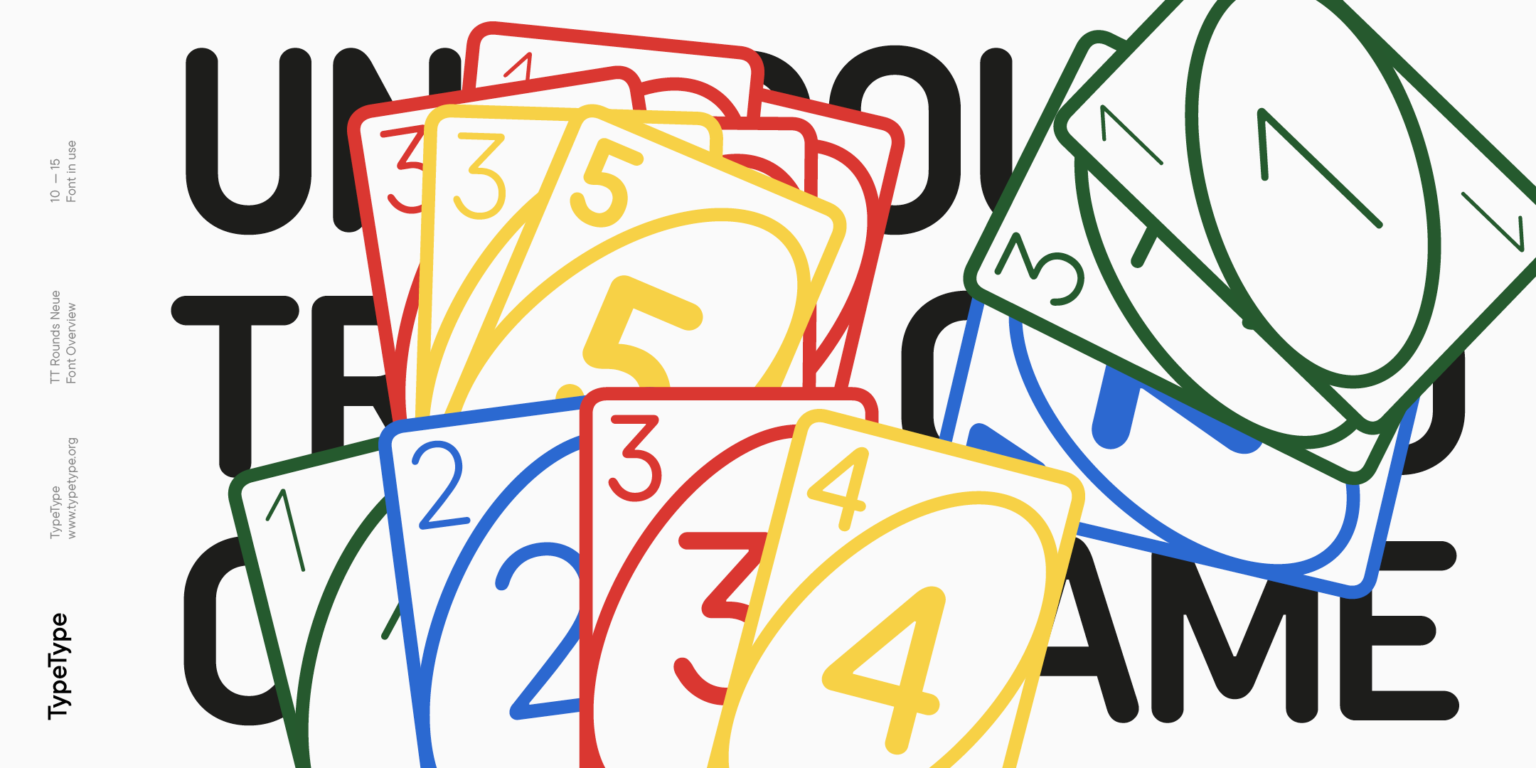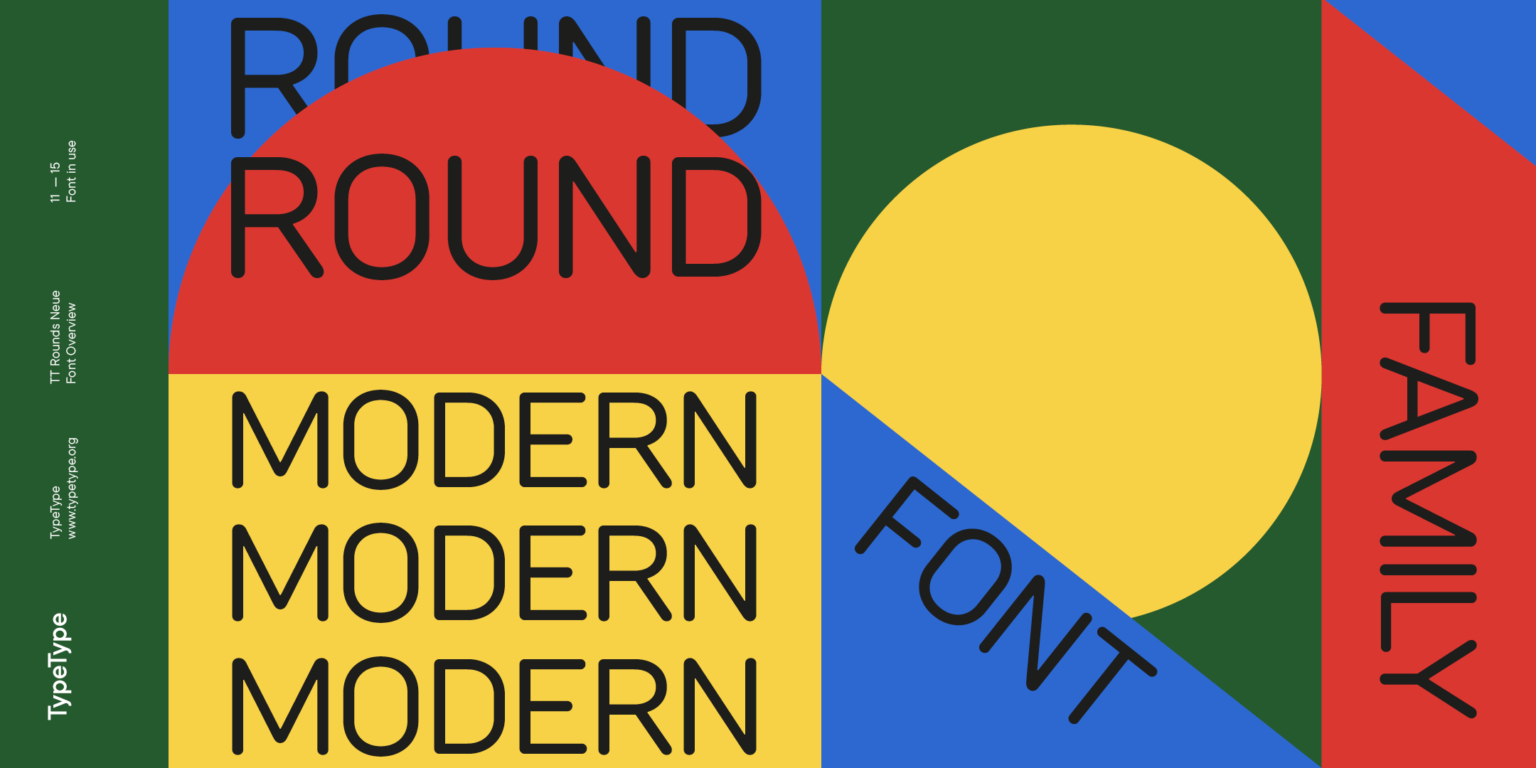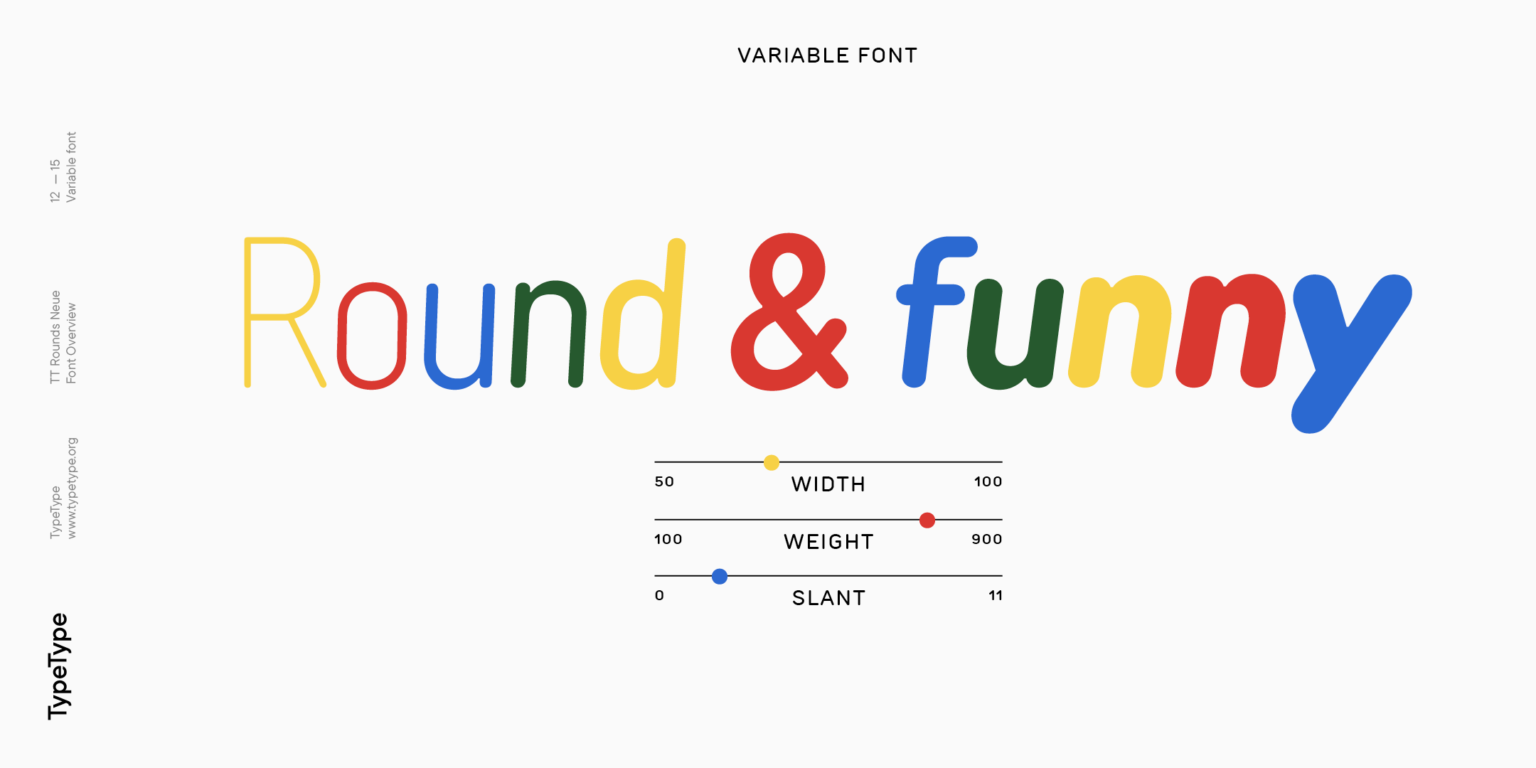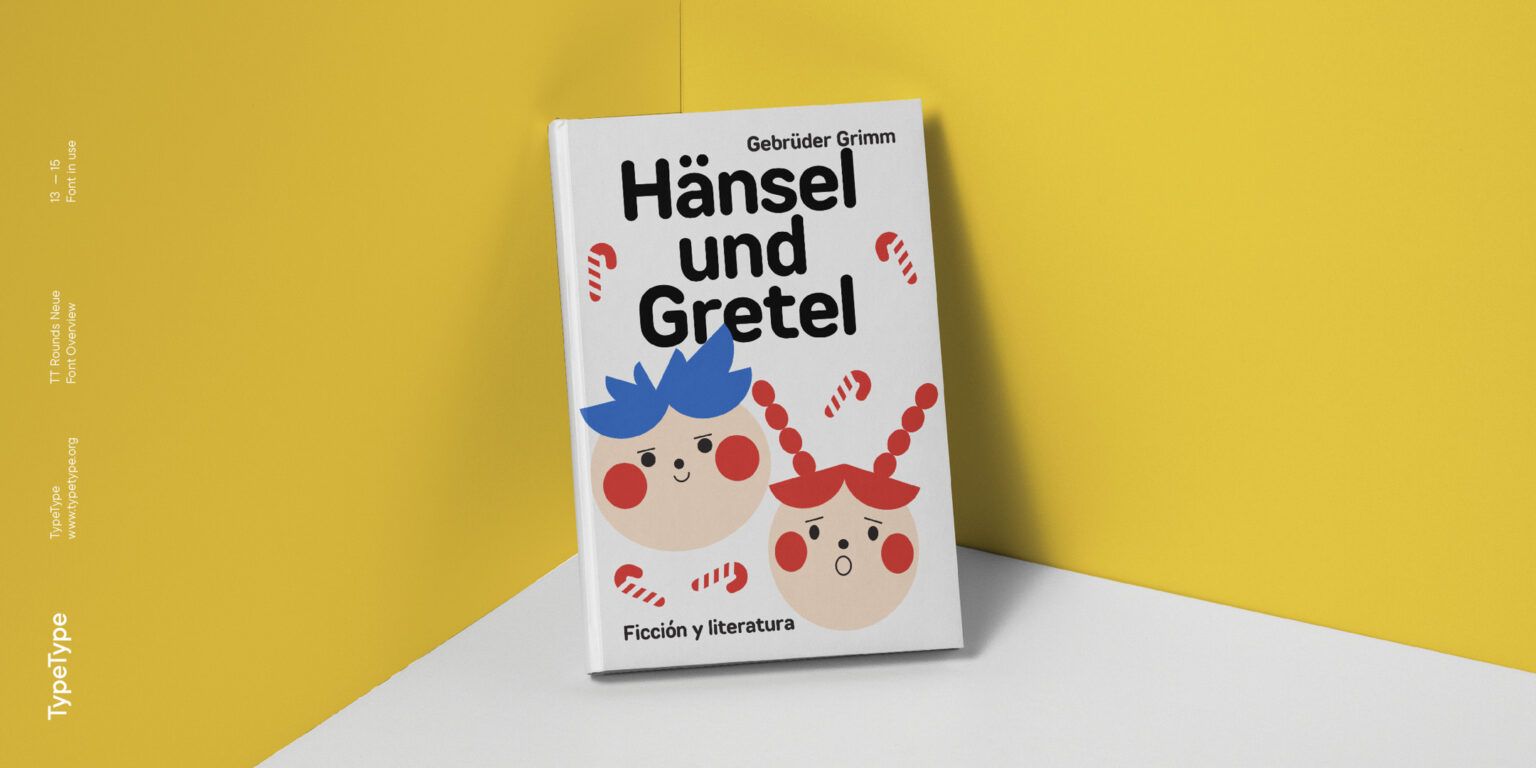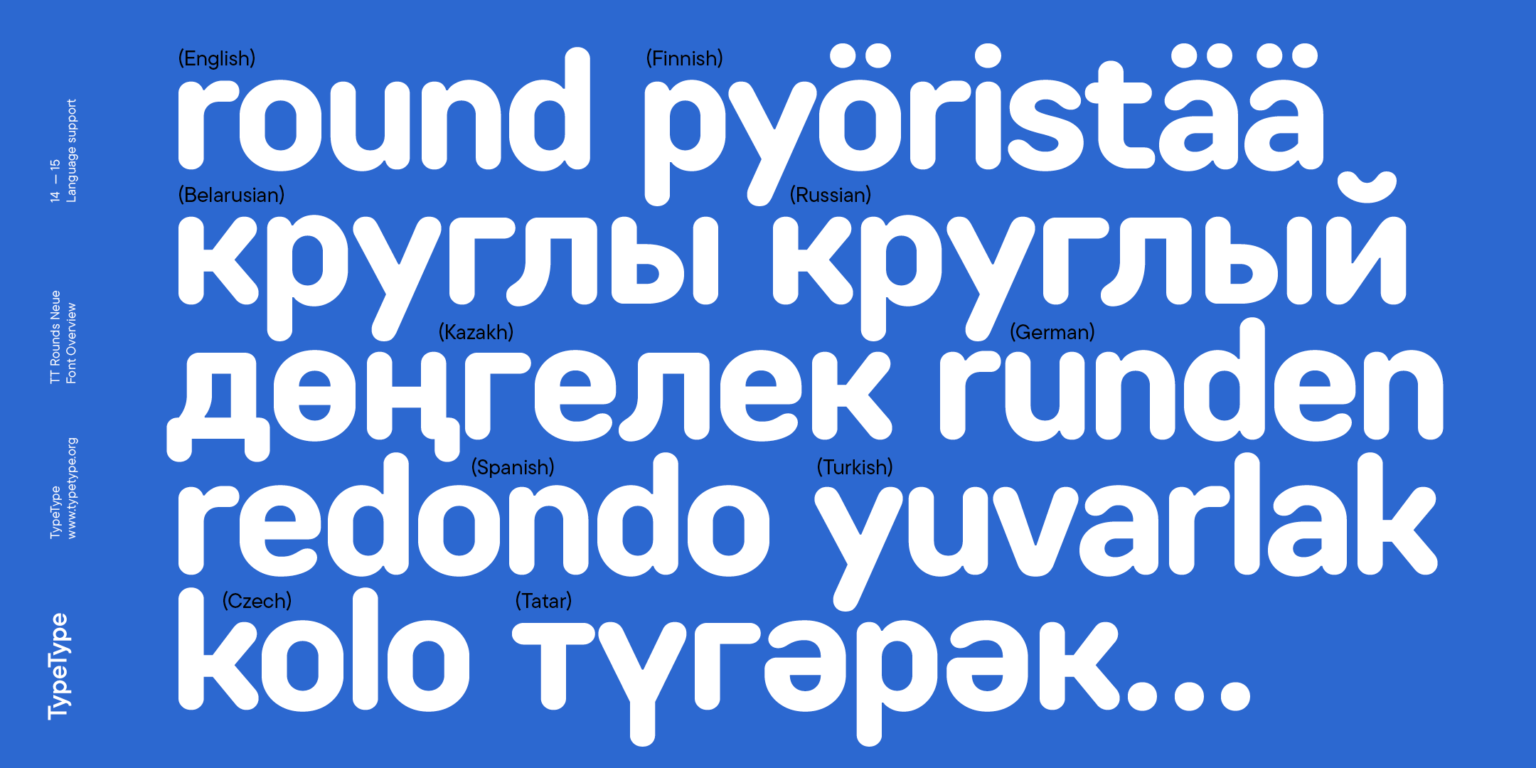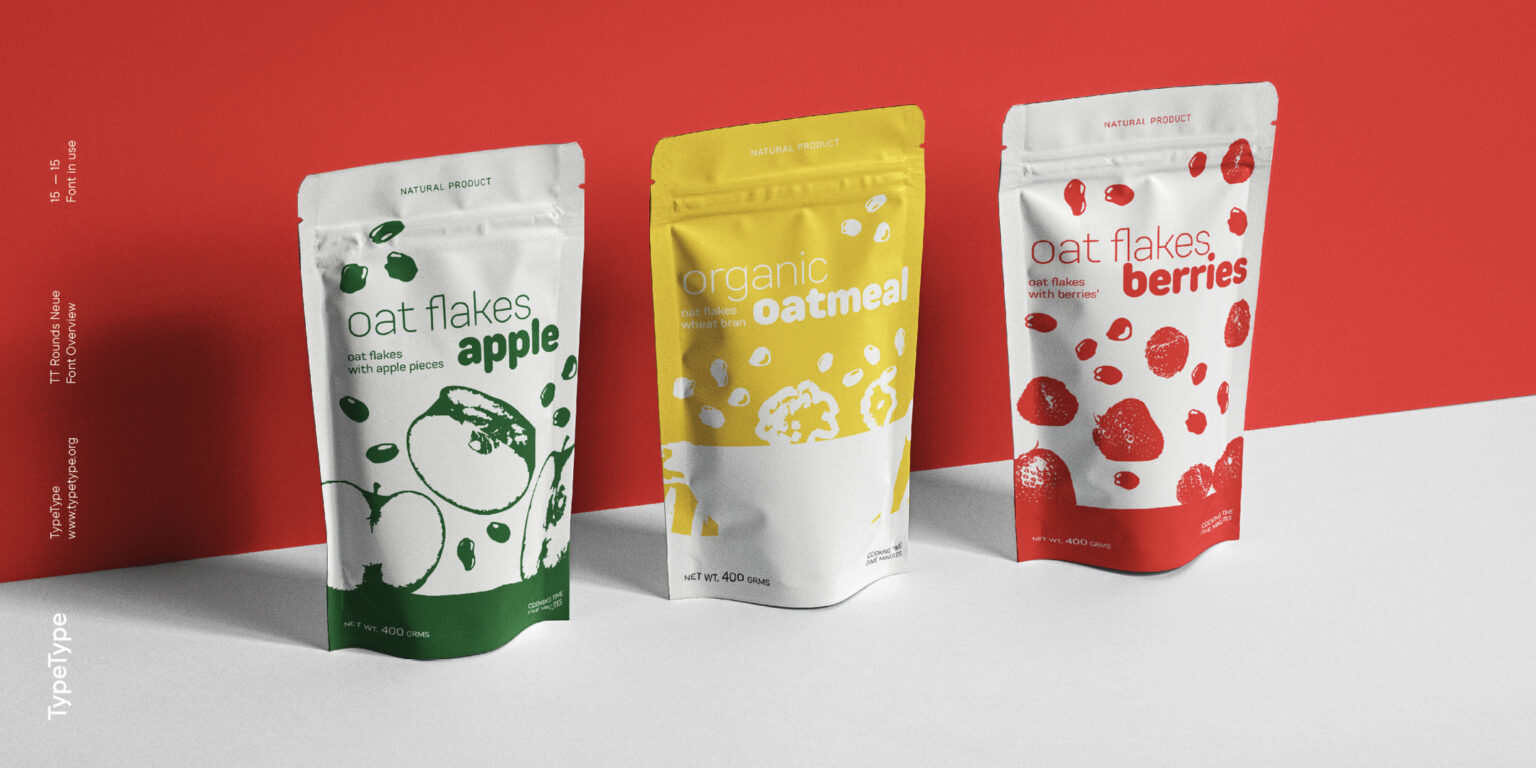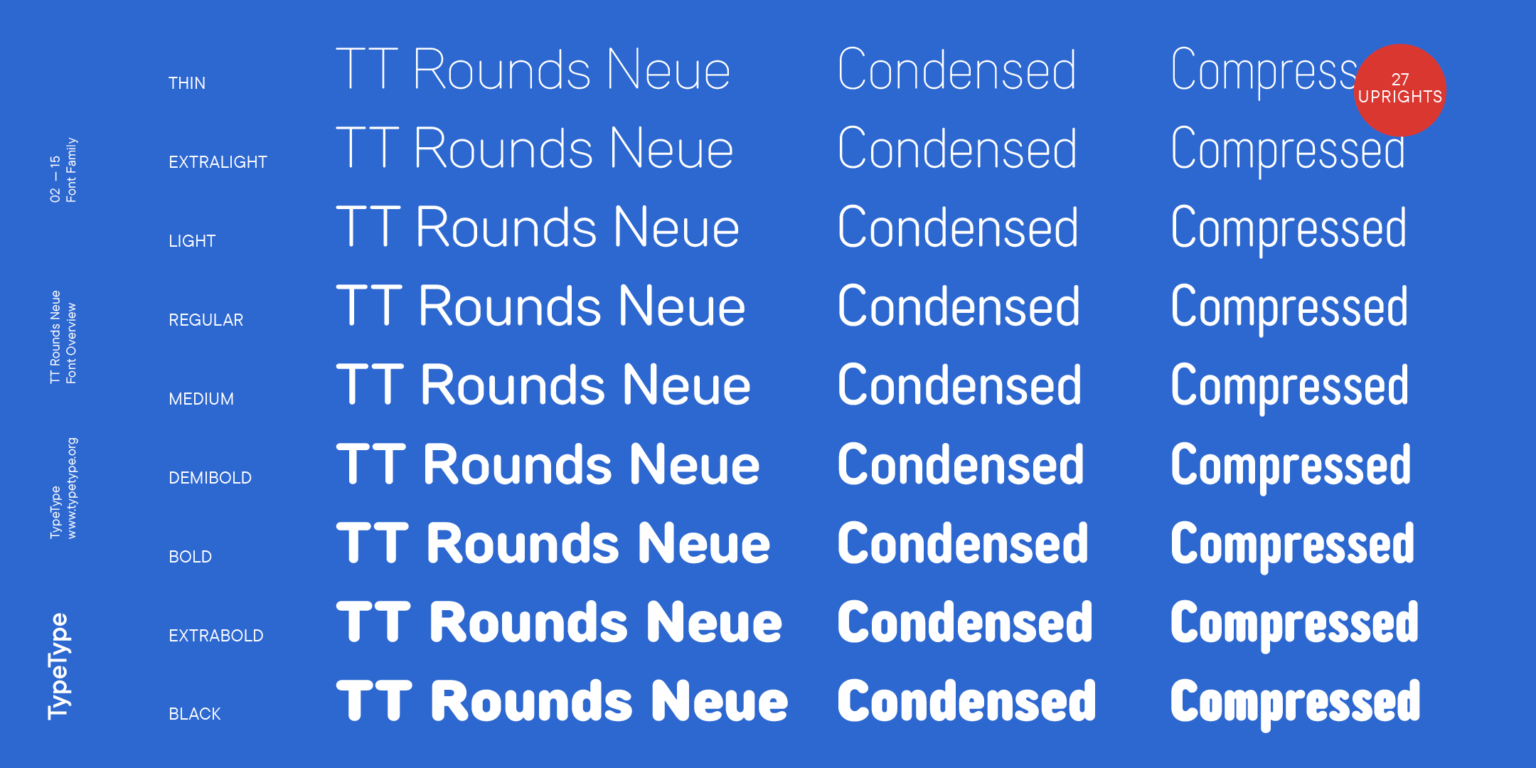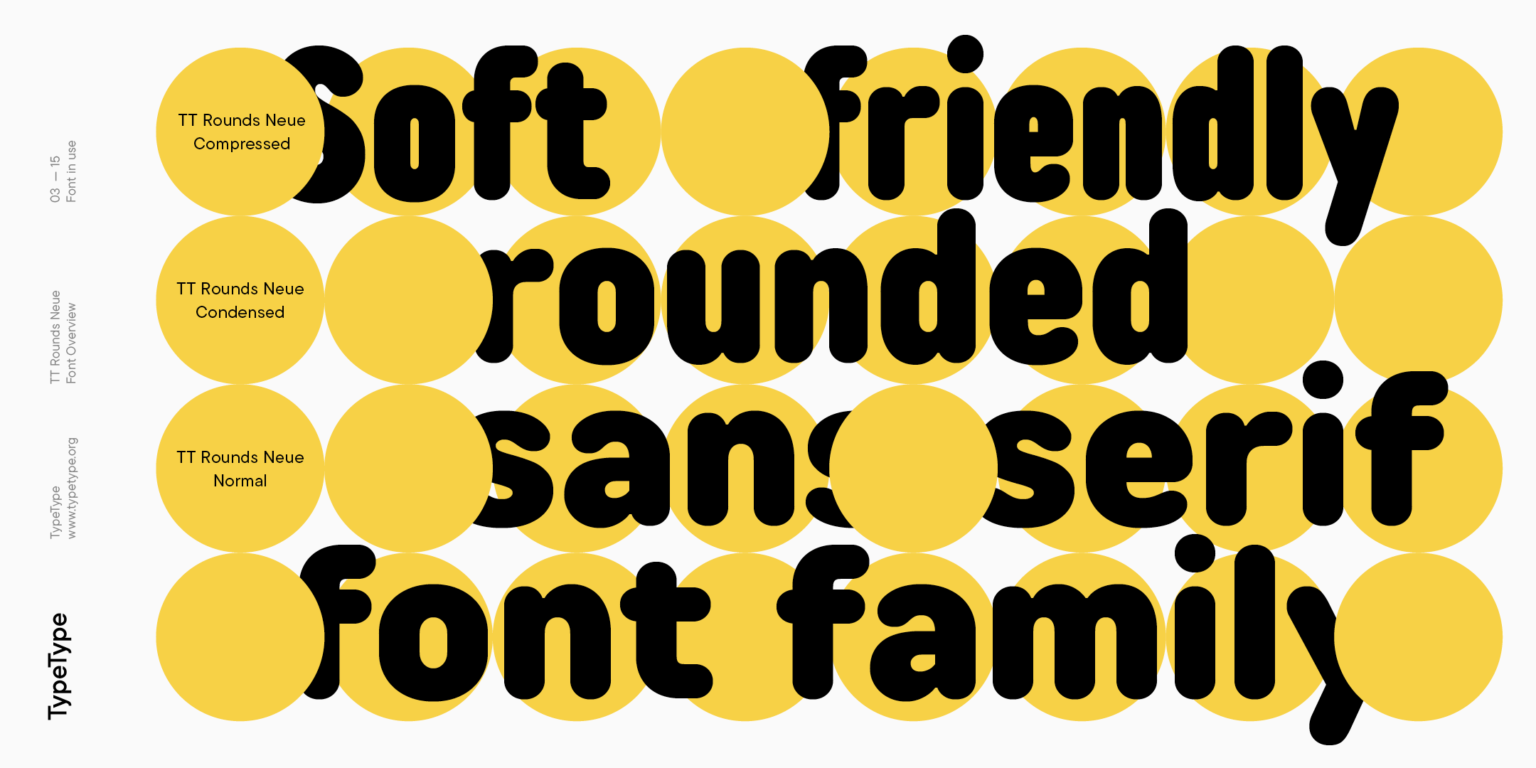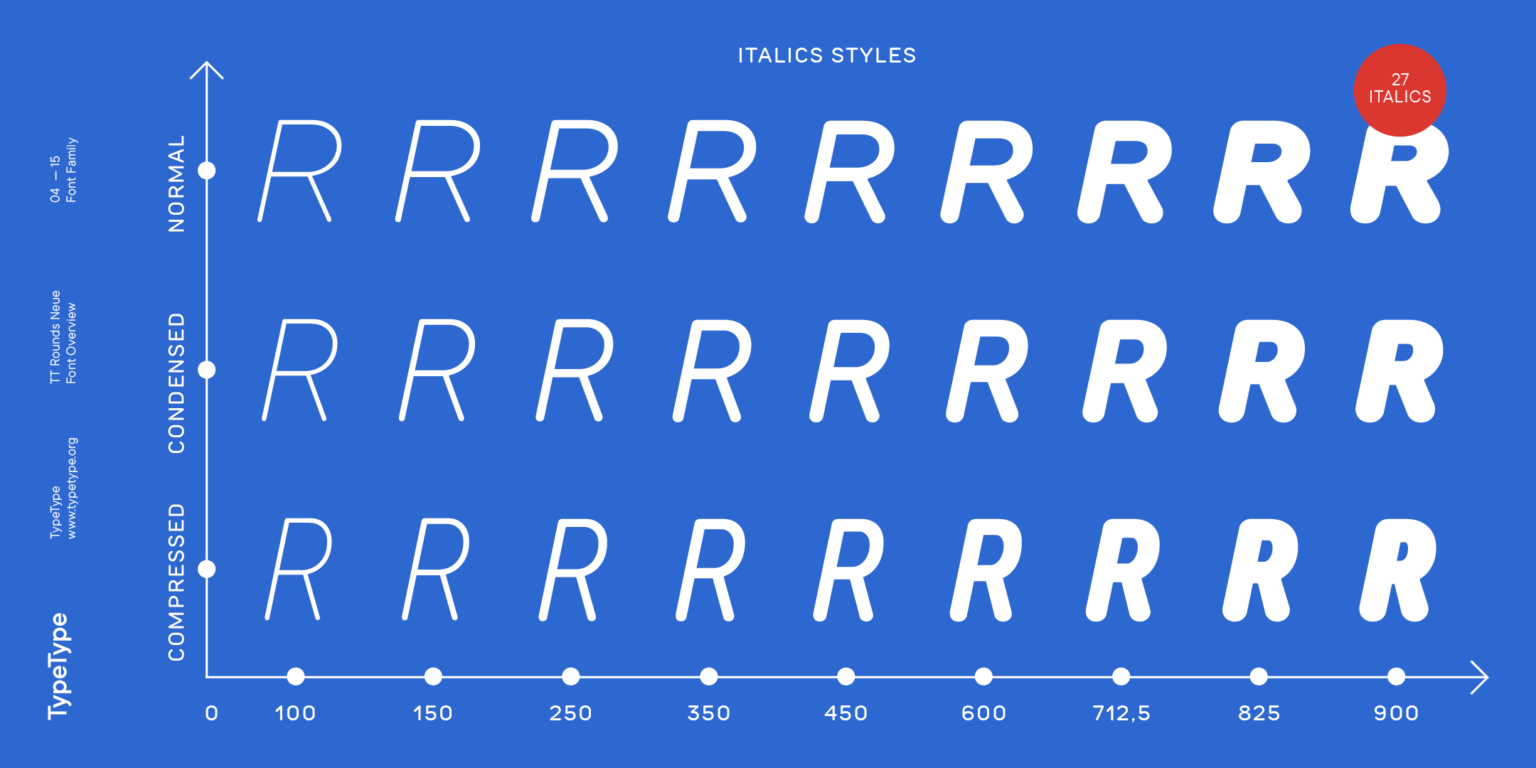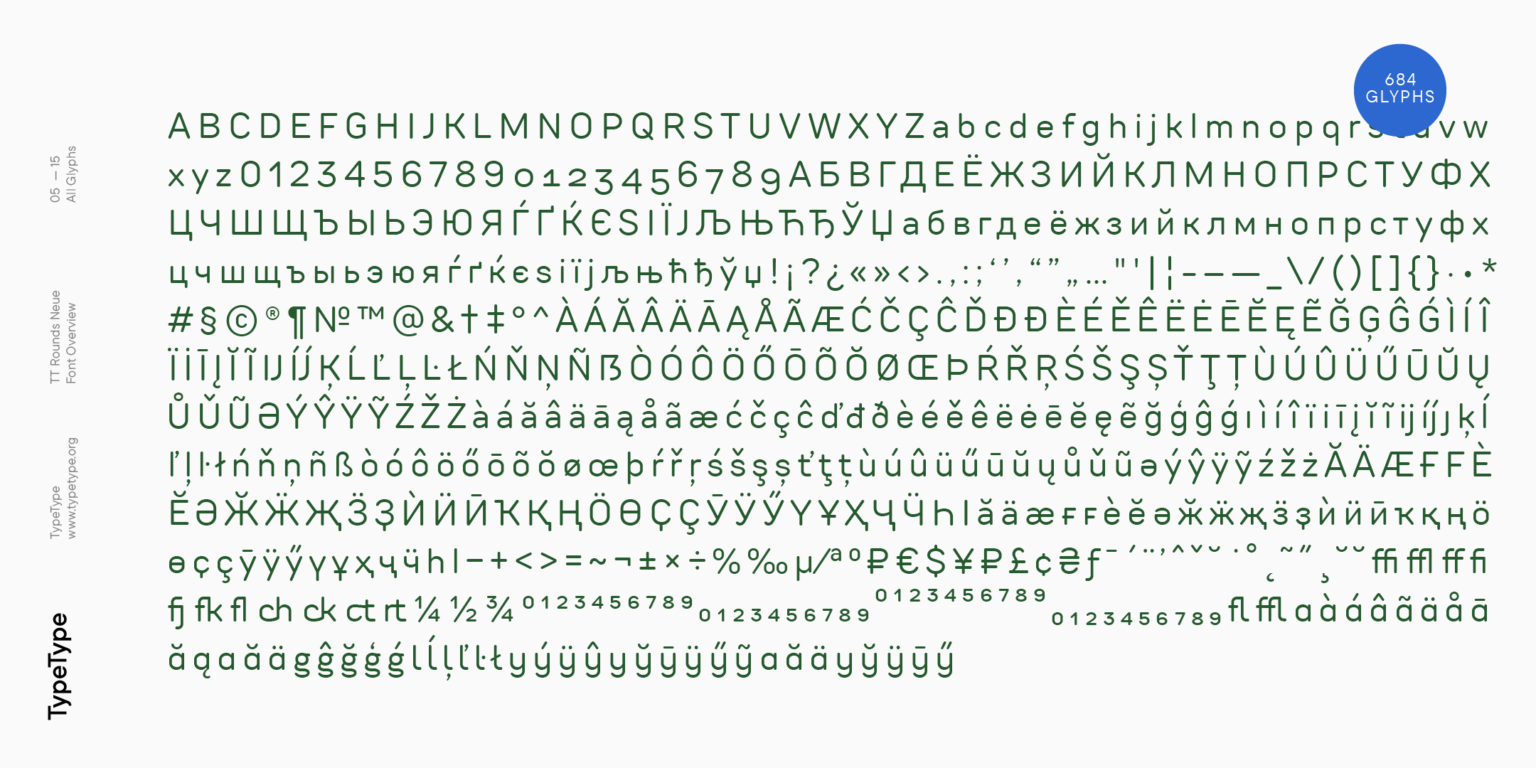
TT Rounds Neue — جروتيسك ناعم وودود بأشكال مستديرة. في الأوزان الرقيقة يبدو بسيطًا وحياديًا، بينما في الأوزان السميكة يصبح أكثر تميزًا وملفتًا.
Soft, friendly, rounded sans serif fontfamily
TT Rounds is a large font family consisting of 3 subfamilies: Compressed, Condensed and Normal. Thanks to its rounded strokes, the font has a very soft and friendly character. In 2022, the font family received a big update, in which we expanded the character set, improved OpenType features, and create a full three-axis variable font.
The fontfamily is ideal for packing oatmeal and baby food
TT Rounds Neue—this is 55 typefaces and a limitless palette of possibilities
حول عائلة الخط TT Rounds Neue
قمنا بتحديث TT Rounds Neue!
TT Rounds Neue — خط غير مذنب ذو أشكال مستديرة. يتمتع بطابع ناعم وودود. في الأوزان الرقيقة، يبدو الخط بسيطًا وحياديًا إلى حد كبير: تصبح النهايات المستديرة للخطوط بالكاد ملحوظة، وتبرز الخطوط المنحنية بشكل رئيسي. في الأوزان الثقيلة، يتضخم TT Rounds Neue ويبرز كل ما فيه من استدارة، مما يضفي عليه ملامح طفولية.